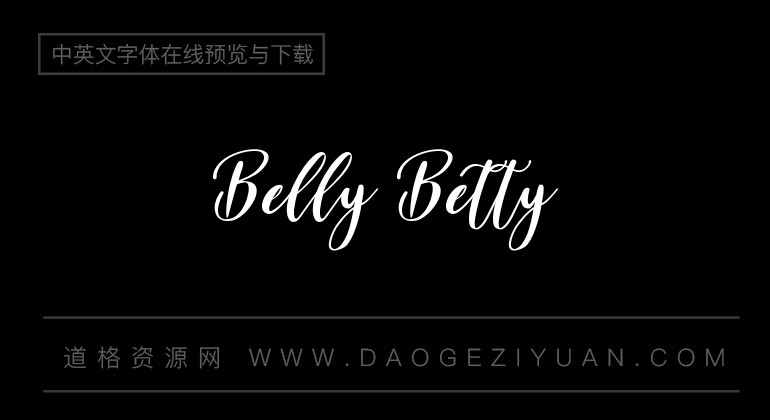
Belly Betty
Belly Betty 是一款由 Creative Market 发布的手写体字体,由美国设计师 Darrin Crescenzi 设计。它拥有柔和而友好的外观,充满活力和温暖的气氛,非常适合用于海报、卡片、T恤和其他印刷品的设计。它包括一系列英文字母、数字和符号,以及英文和拉丁文的支持,可以在 Mac 和 Windows 系统上使用。
Belly Betty是一款非常不错的手写艺术字体,具有很好的视觉感,适合于文化类的宣传设计、商业类品牌的广告和产品包装设计以及个性化文字排版等较多场景。
Belly Betty字符映射图